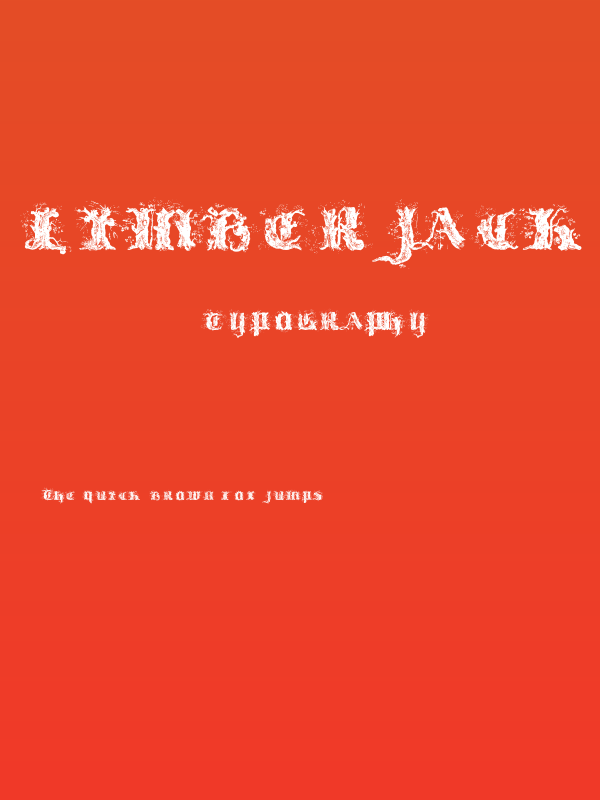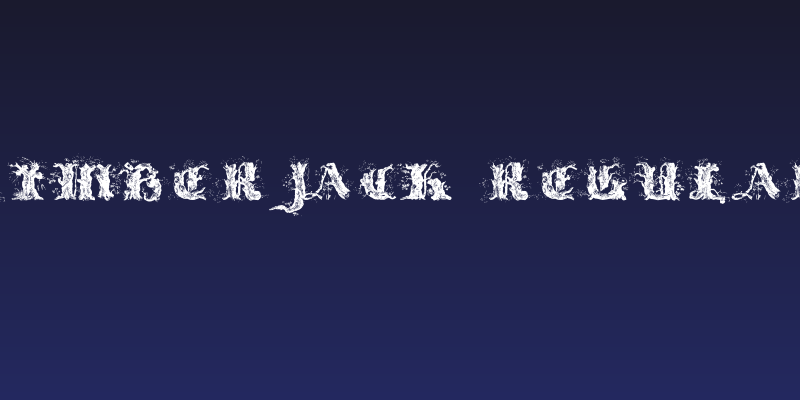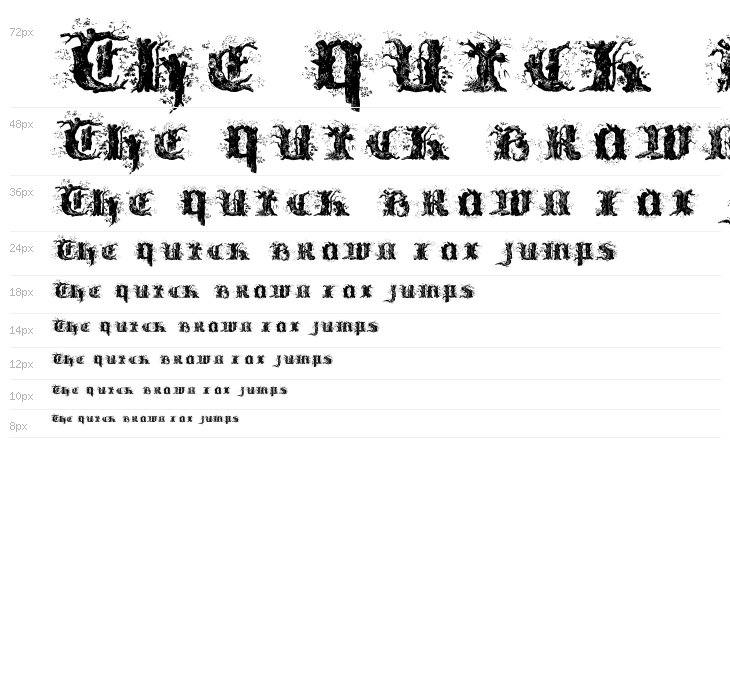
Limberjack Regular Font
✎ Gothic
| Progetti proposti | Ideal for album covers, posters, gothic-themed events, or any project needing a dramatic, artistic touch. |